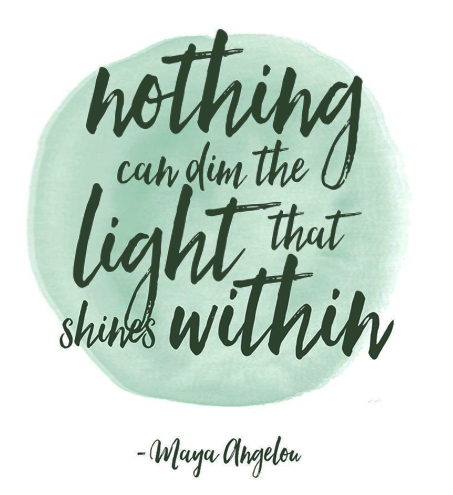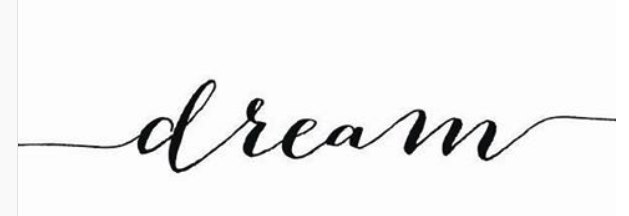
Welche Schriften sind das?
Mal wieder ein paar Schriftarten deren Namen ich gerne wüsste!
Diese Script-Fonts sind zur Zeit sehr im Trend, sodass man nicht einfach erkennen bzw. identifizieren kann, um welche Schrift es sich handelt.